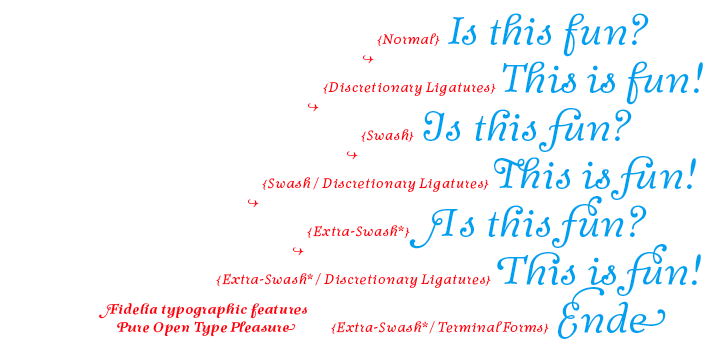
The Sans – passende Script font gesucht
ich suche für eine Hochzeitseinladung und alles was an Drucksachen dazu gehört
(Fließtext The Sans)
eine passende schöne Script Font für die Überschriften.
Zur TheSans finde ich folgende Fonts recht stimmig:
Ansonsten sind auch hier einige denkbare zu einem günstigen Preis zu haben, welche ich für das Thema sogar noch geeigneter halte:
Dazu würde möglicherweise eher etwas geometrisches oder statisches passen:
Kommt halt auch immer etwas darauf an, welchen Stil man anstrebt – französische Leichtigkeit, englische Eleganz, etc. und wie das Paar so drauf ist.
eine passende schöne Script Font für die Überschriften.
Wenn Du Individualität möchtest, lass Dir doch was schönes vom Kalligraphen schreiben.
... oder nimm selber den Pinsel in die Hand  :hammer:
Hier auch gratis!
Wobei ... wenn ich mir schon die Verbindung ›Es‹ angucke  :shock: